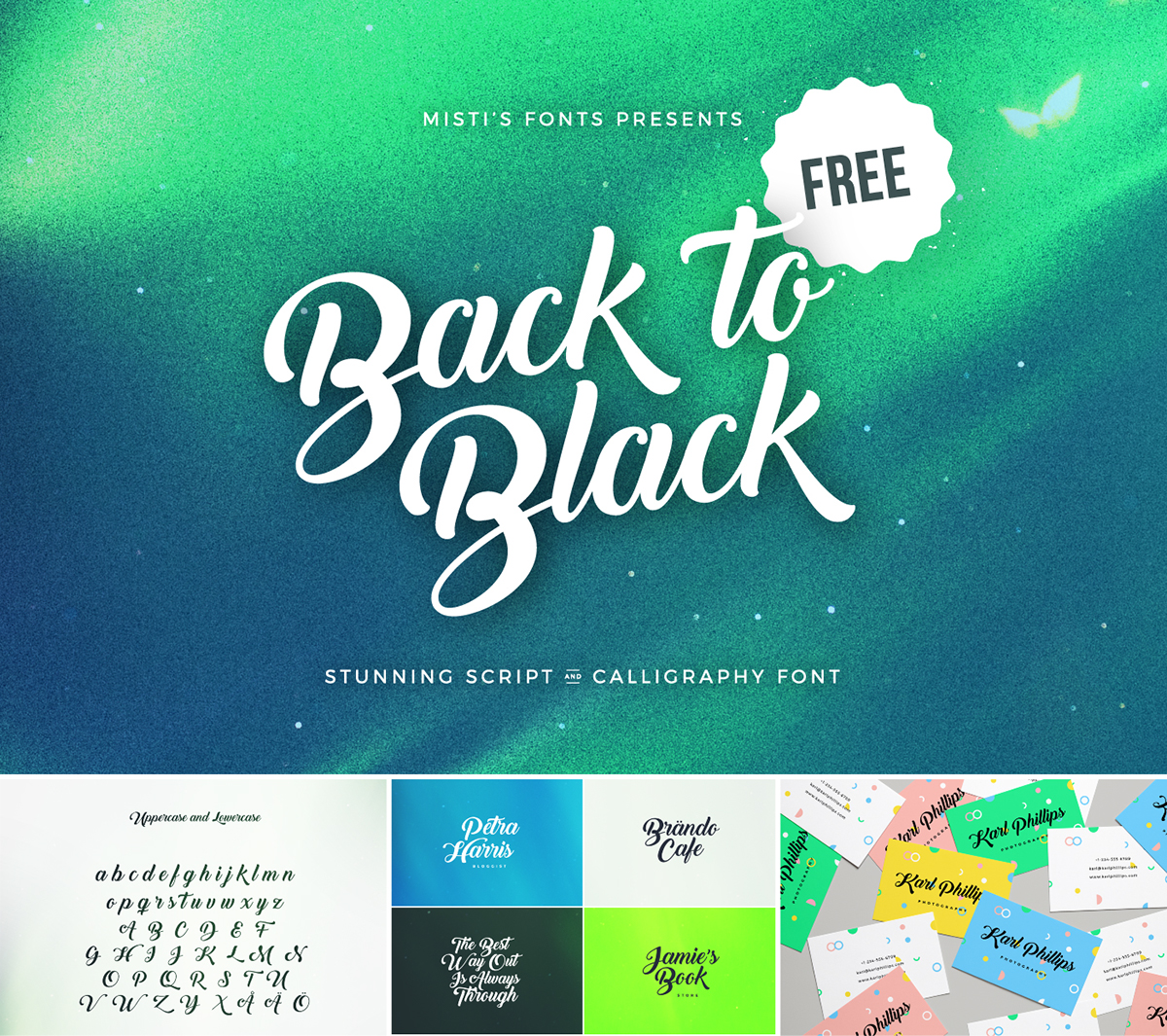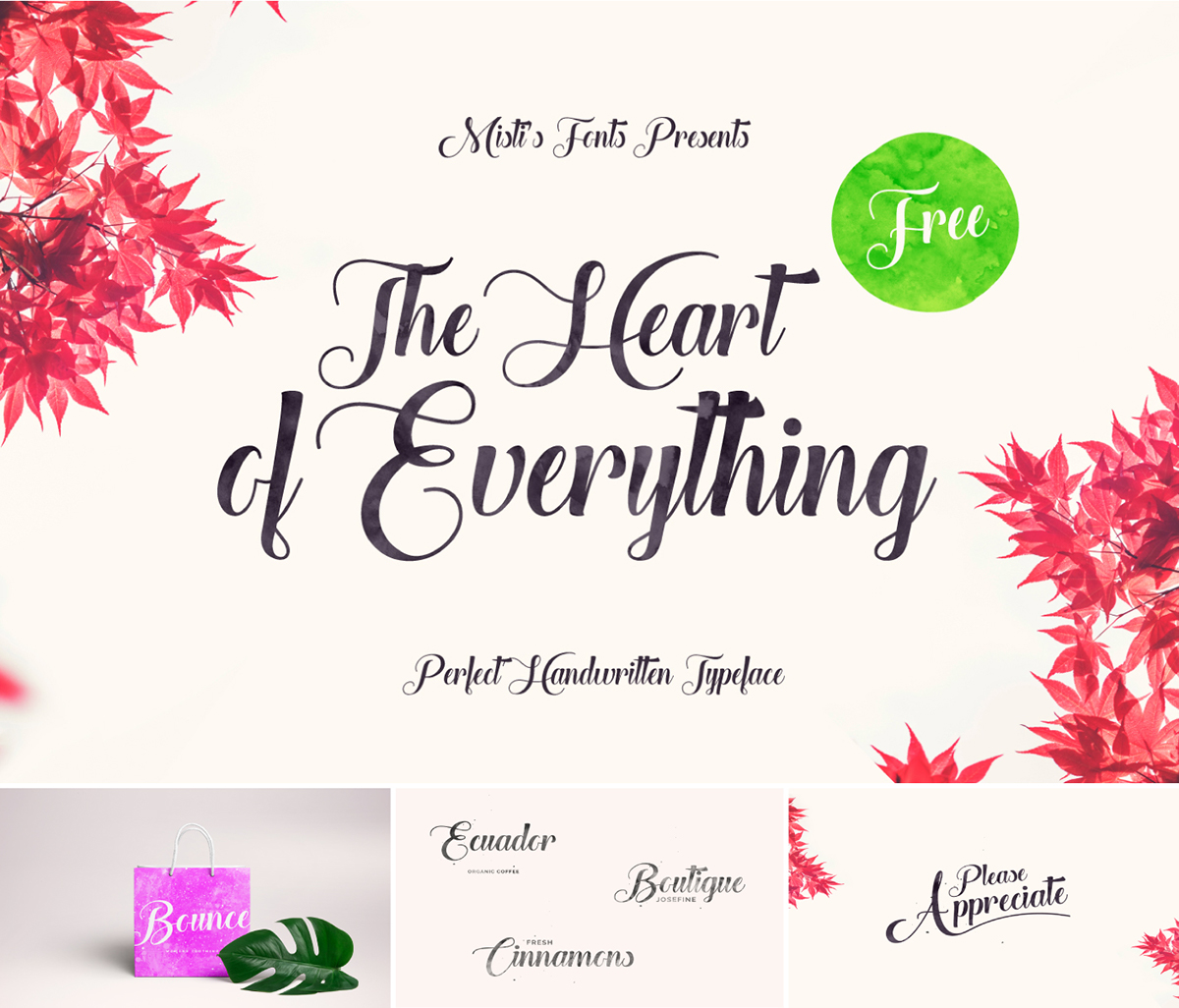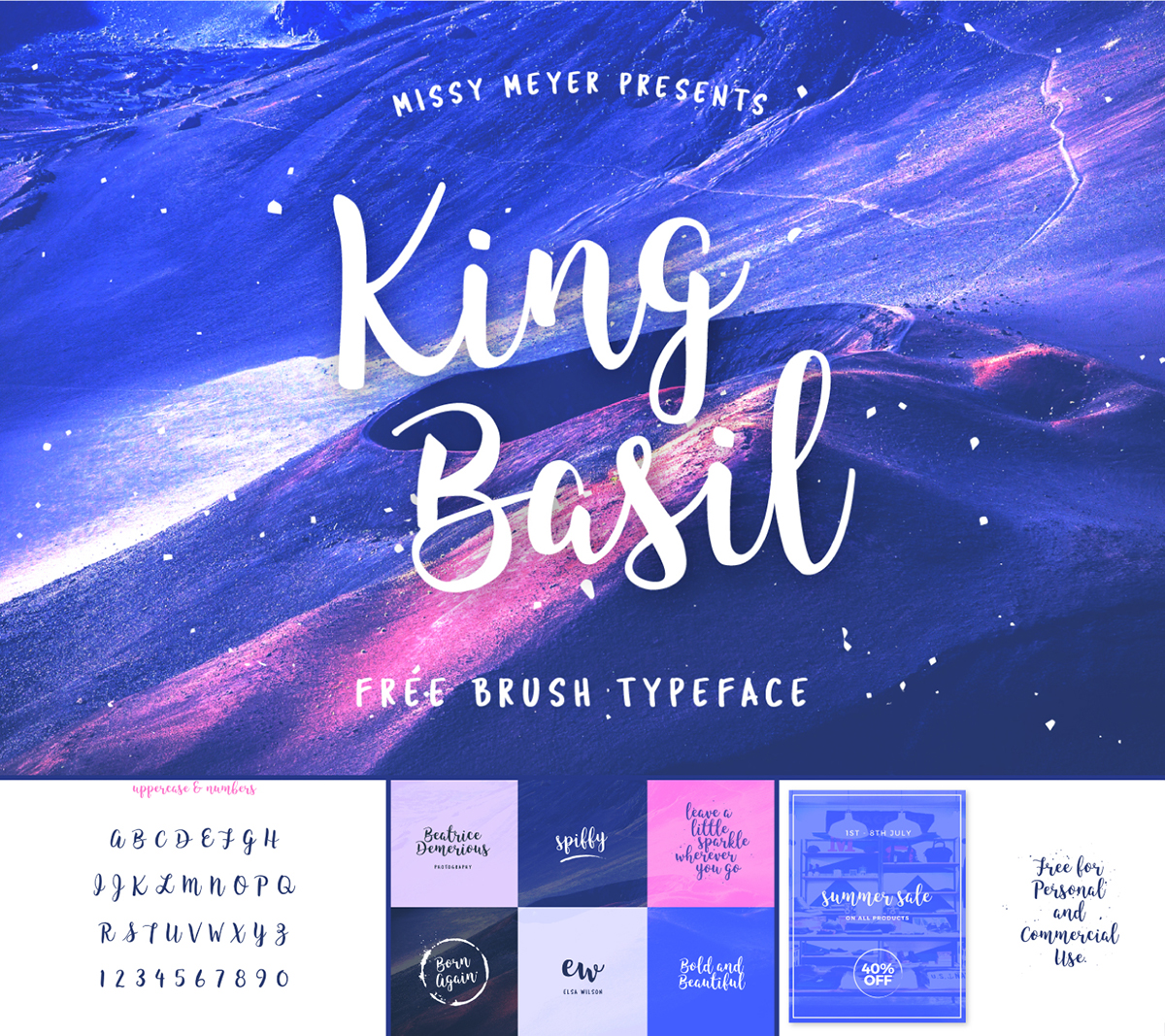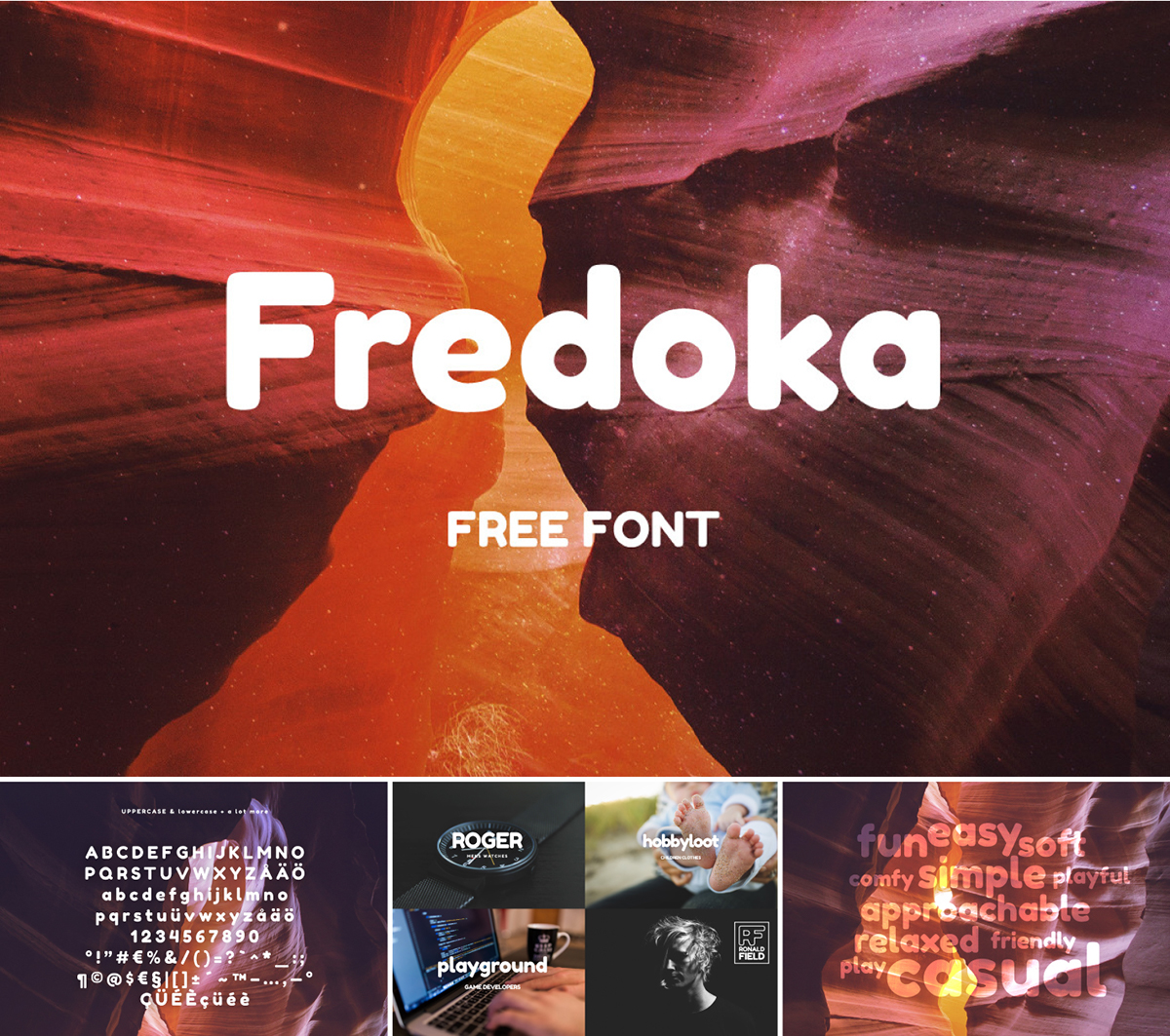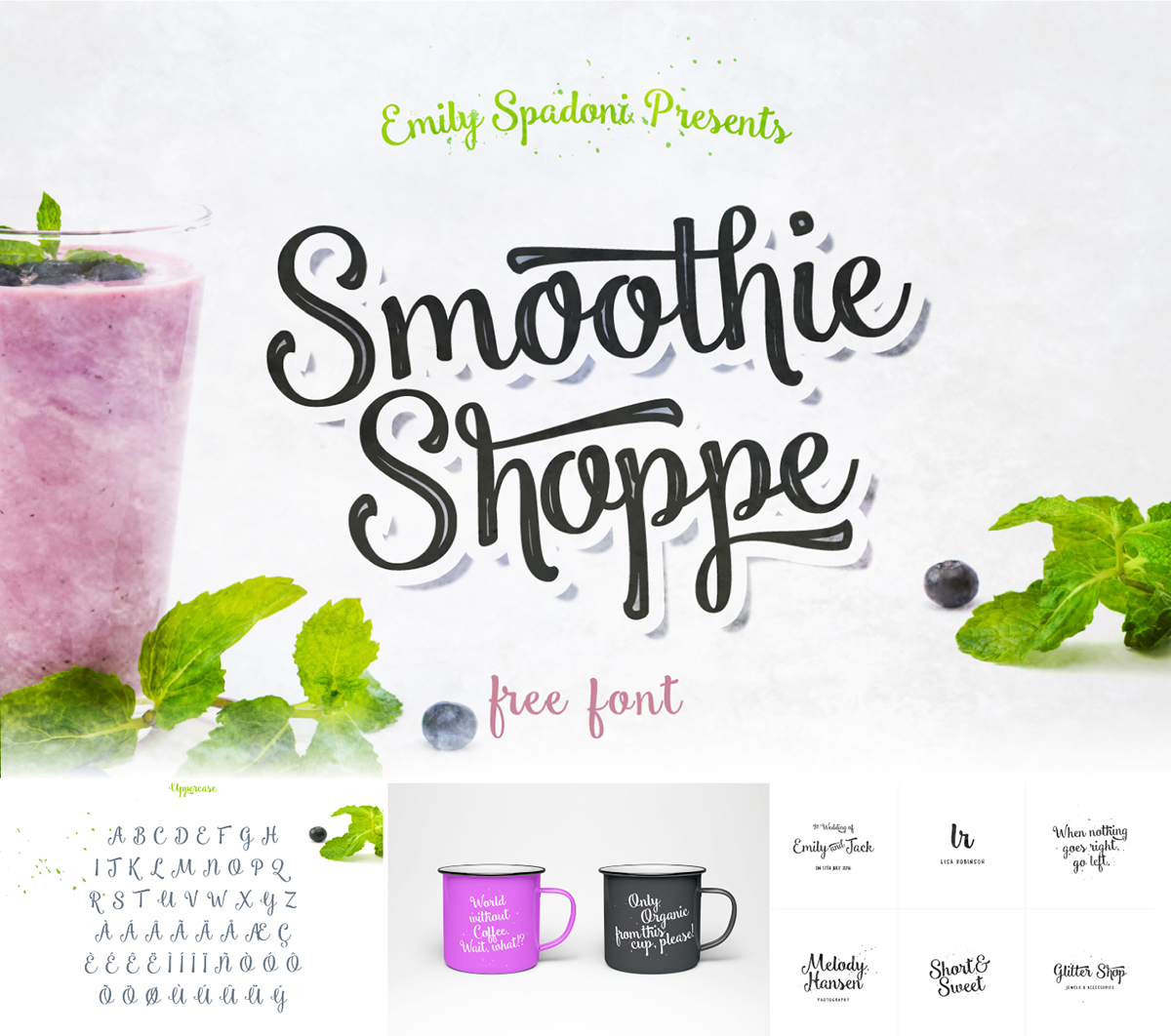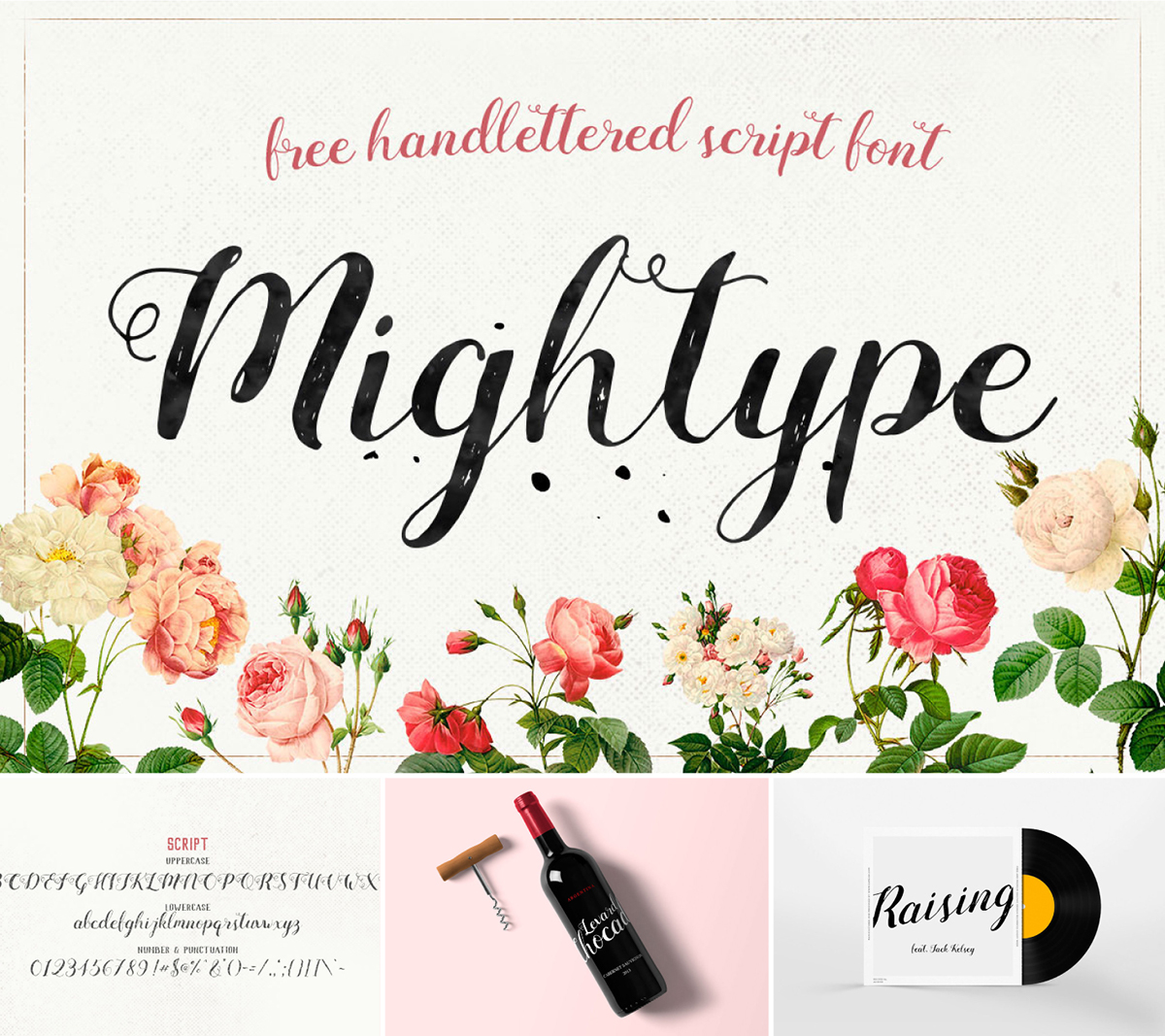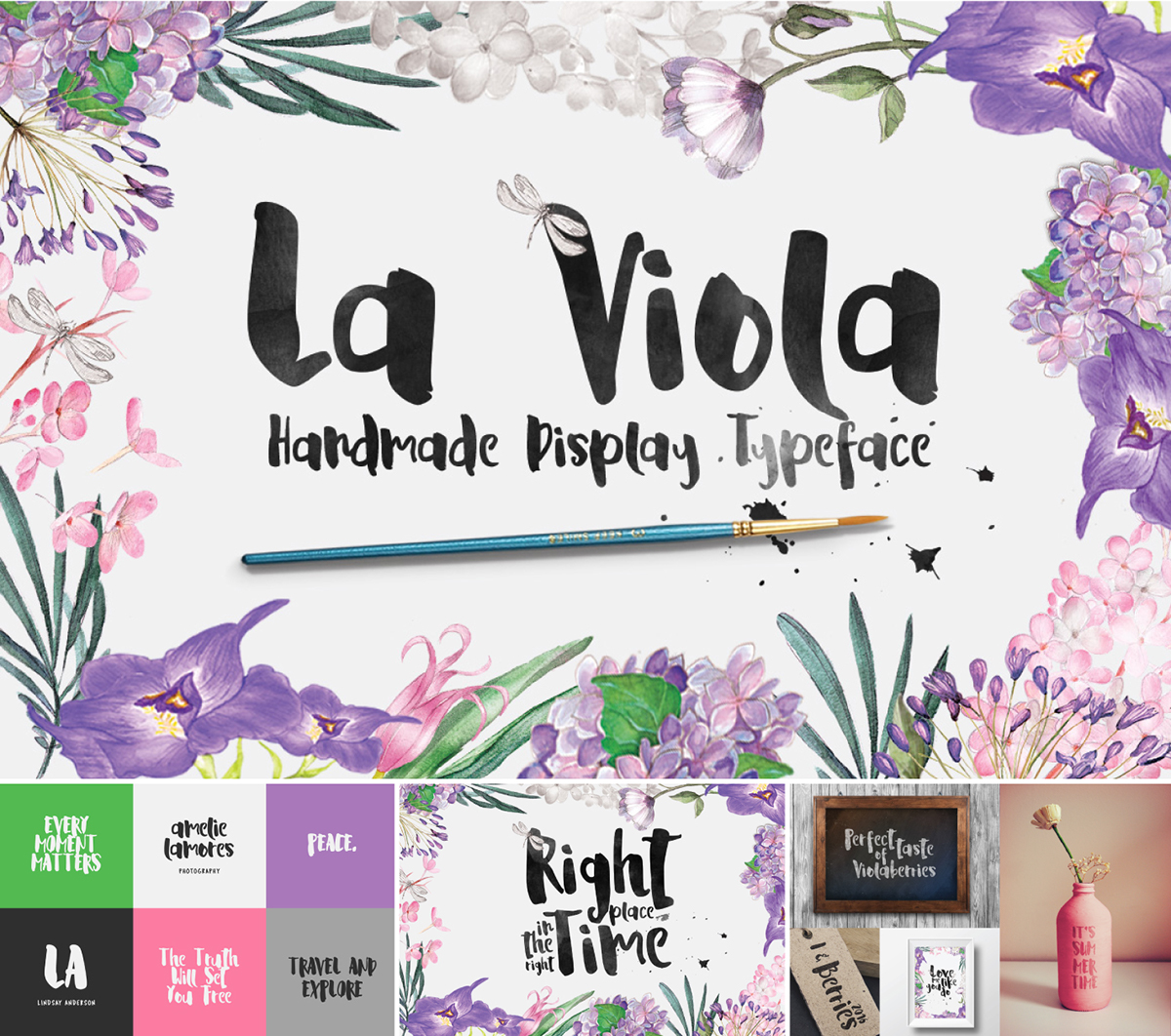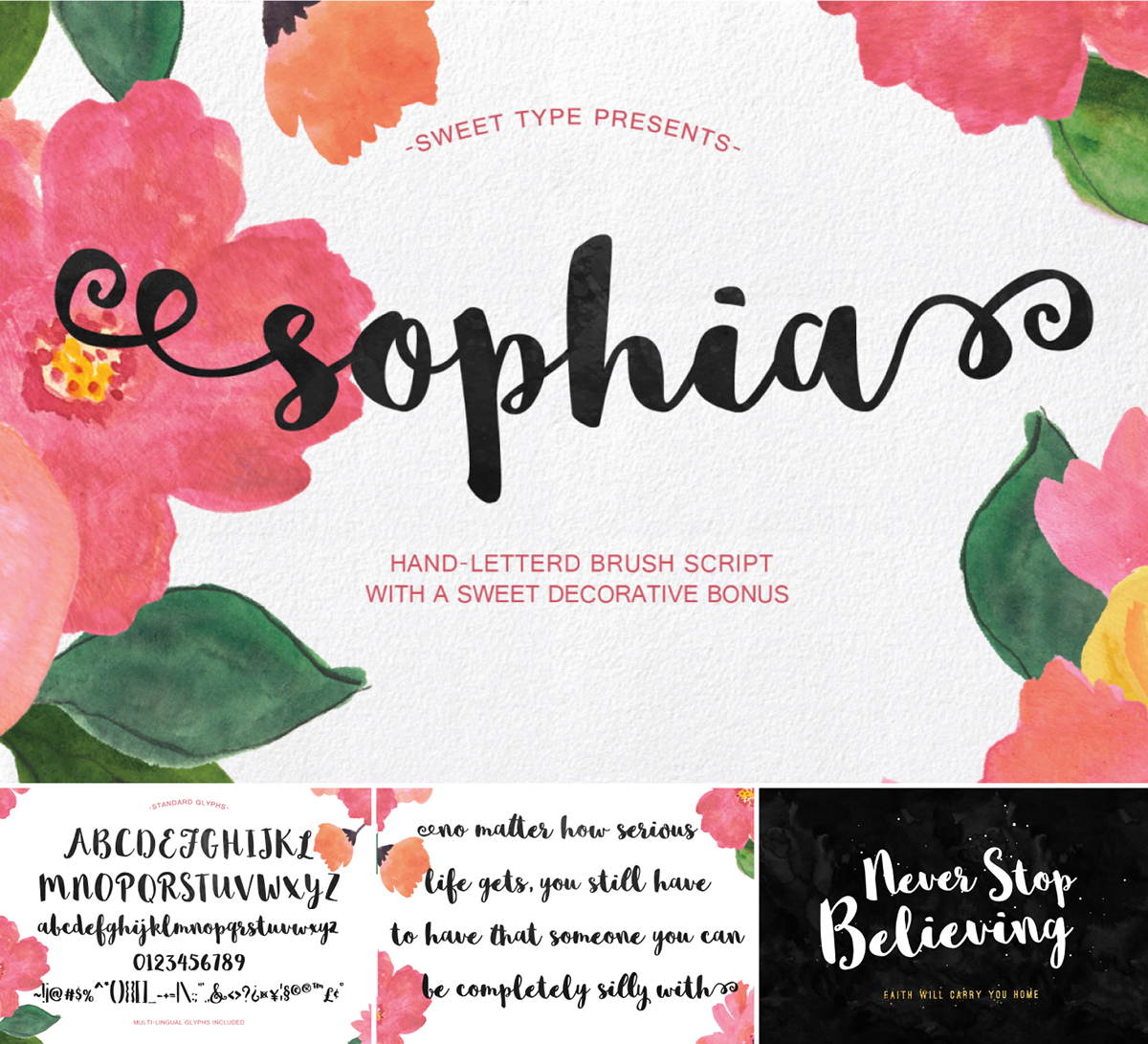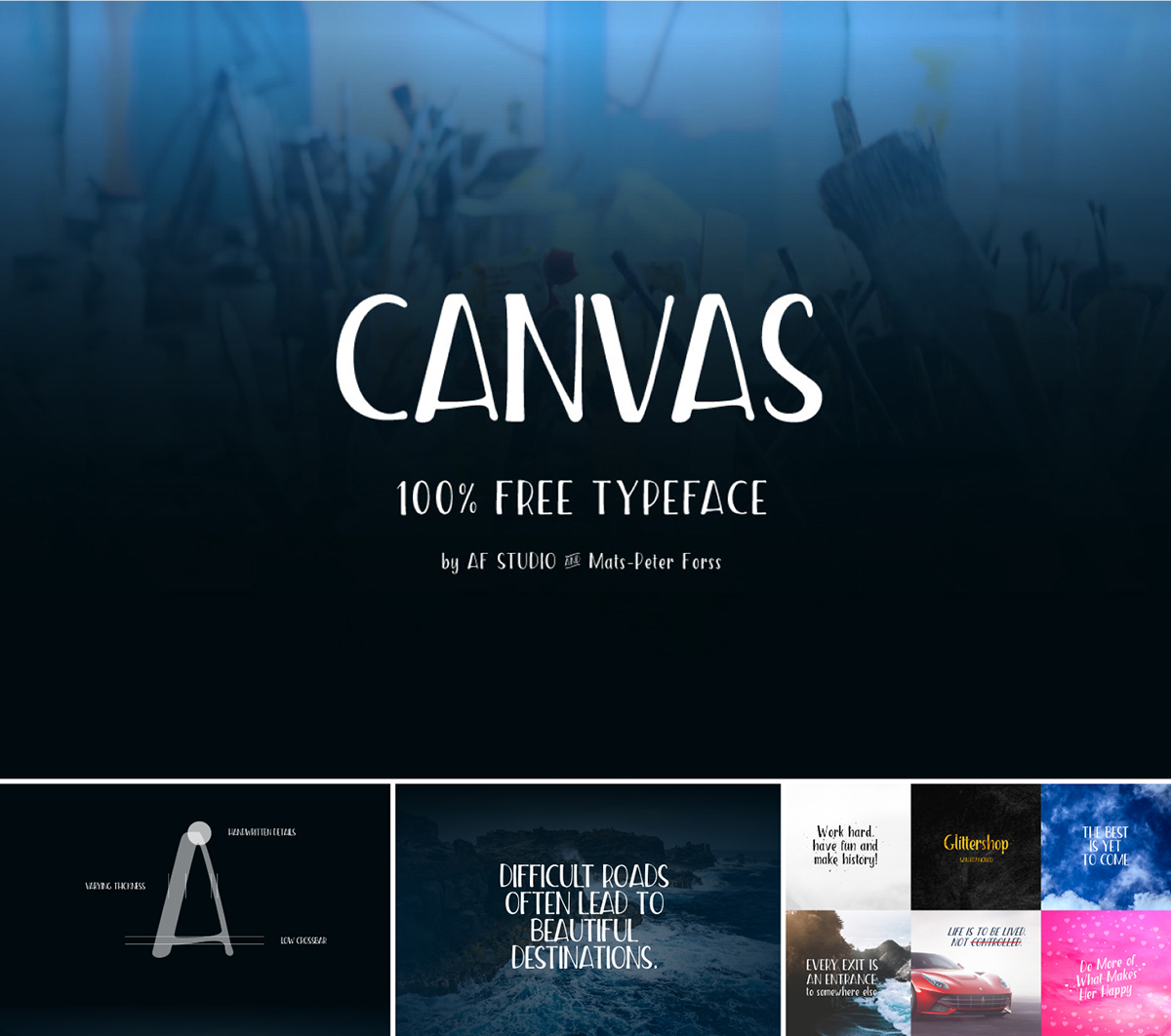
Mats-Peter Forss, đến từ Phần Lan, một người thiết kế chuyên nghiệp trong lĩnh vực typography, hiện anh là Founder của Creative Booster.
Back to Black – Free Creative Font
by Misti’s Fonts
The Heart of Everything
by Misti’s Fonts
King Basil – Free Script Brush Font
by Missy Meyer
Fredoka – Free Rounded and Bold Fonts
Smoothie Shoppe – Free Script Font
by Emily Spadoni
Mightype Script – Free Handlettered Font
by AF Studio
La Viola – Free Handmade Display Font
Sophia – Free Handlettered Brush Script Font
by Emily Spadoni
Canvas – Free Condensed Font
by AF Studio
Bravery – Free Display Font
by Suke Toejoeh
Michelle – Free Handmade Script Font
by Noe Araujo